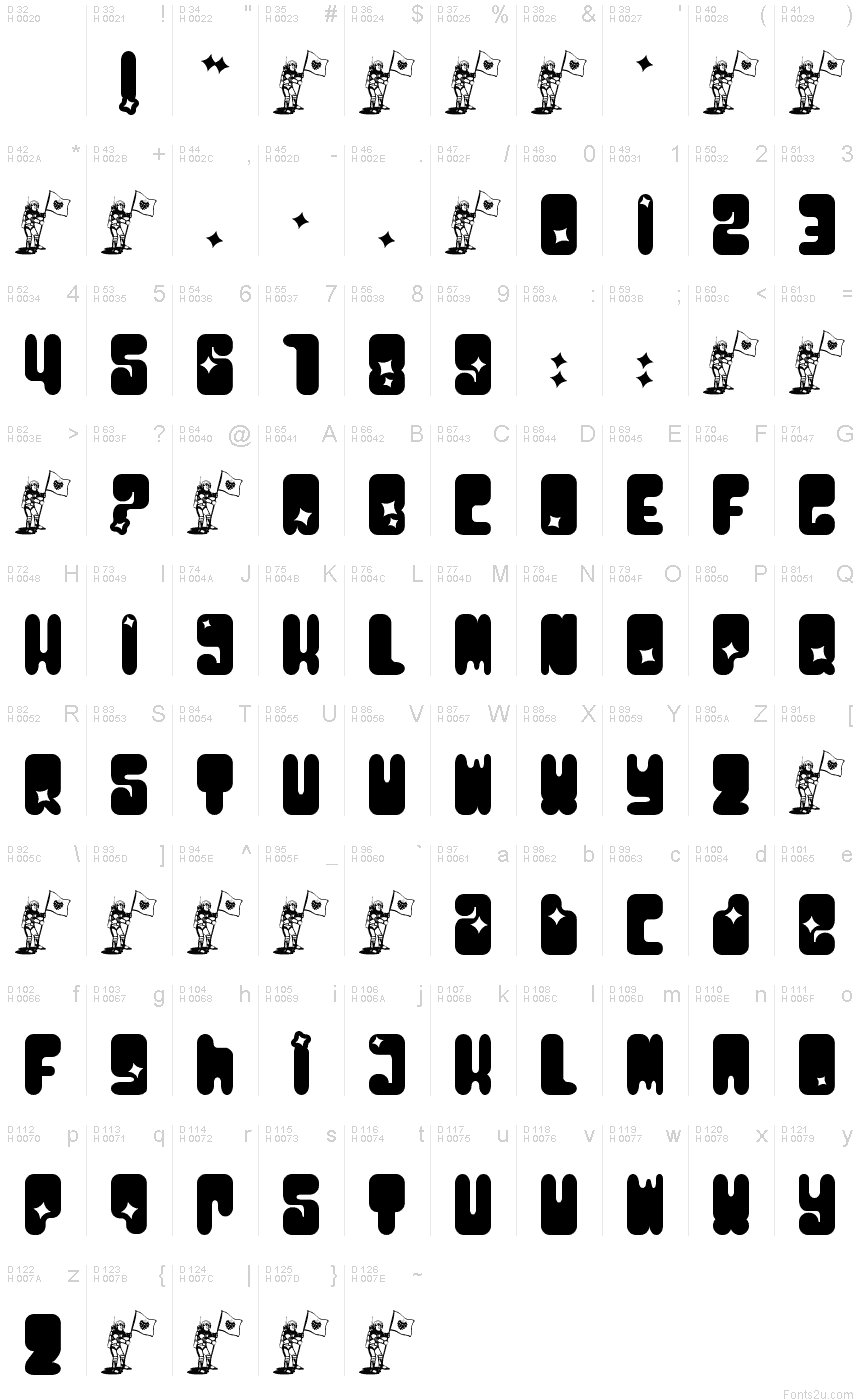
MoonPie Cadet Good von Font-a-licious Fonts ist eine kostenlose Groovy-Display-Schrift mit großen, abgerundeten Buchstabenformen. Breite Striche und weiche Ecken verleihen dem Schriftbild eine gummiartige, aufgeblasene Silhouette. Kleine sternförmige Aussparungen setzen in mehreren Formen Akzente und sorgen für ein Detail im Space-Age-Stil.
Retro-Süßwarenmarken, Scherzartikel-Läden und verspielte Lebensmittelverpackungen könnten eine Identität um die vollen Formen herum aufbauen. Das Sternmotiv passt zudem zu Kinderunterhaltung und Cartoon-Merchandise, besonders wenn die Schrift Teil eines illustrierten Abzeichens oder Maskottchen-Designs wird. Verpackungen sind ihr stärkster Einsatzbereich, da die Buchstaben an geformte Süßigkeiten erinnern und sich bereits wie einfache Produkt-Icons verhalten.